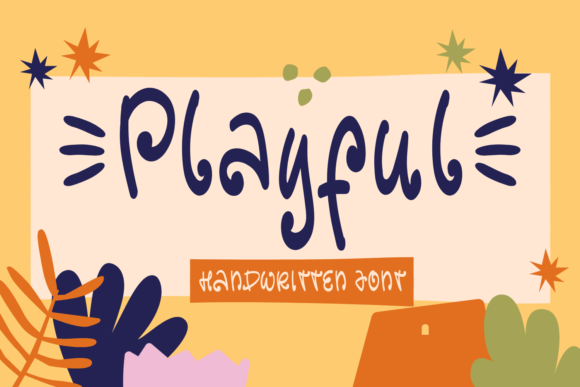
Playful - это милый и причудливый рукописный шрифт.
Он воплощает игривость и подлинность и идеально подходит для любого детского мероприятия или школьного проекта.